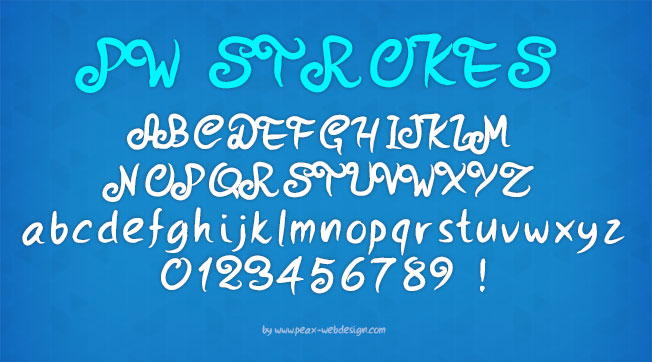
PW Strokes, police manuscrite fluide .ttf
Voici PW Strokes, la nouvelle police de caractères de Peax Webdesign. Cette typo est plutôt épaisse et bien lisible dans toutes les tailles. Elle intègre également les lettres accentuées. Elle est caractérisée par des pointes sur chaque lettre ainsi que des queues en tourbillon sur les majuscules, ce qui pourra faire de PW Strokes une police adaptée aux posters et gros titres. A tester !